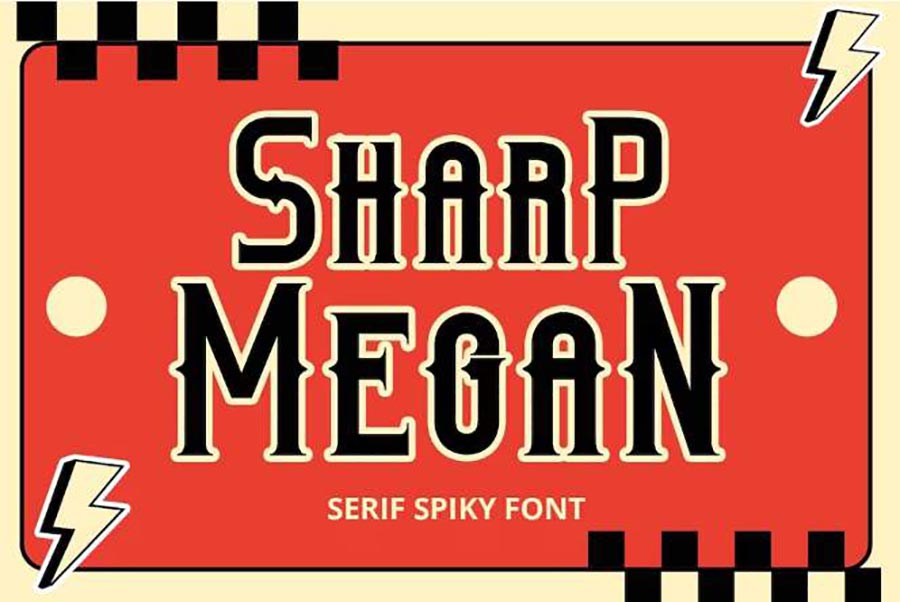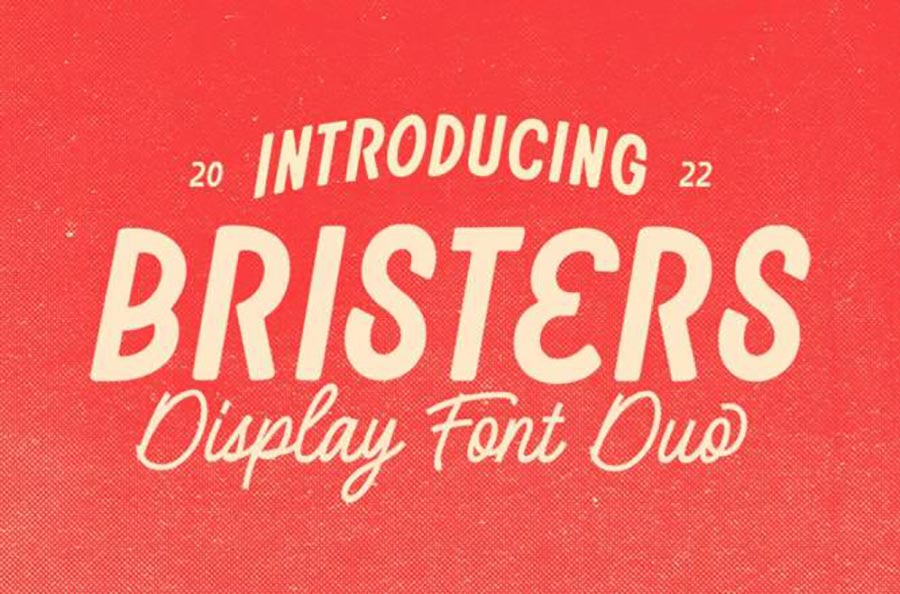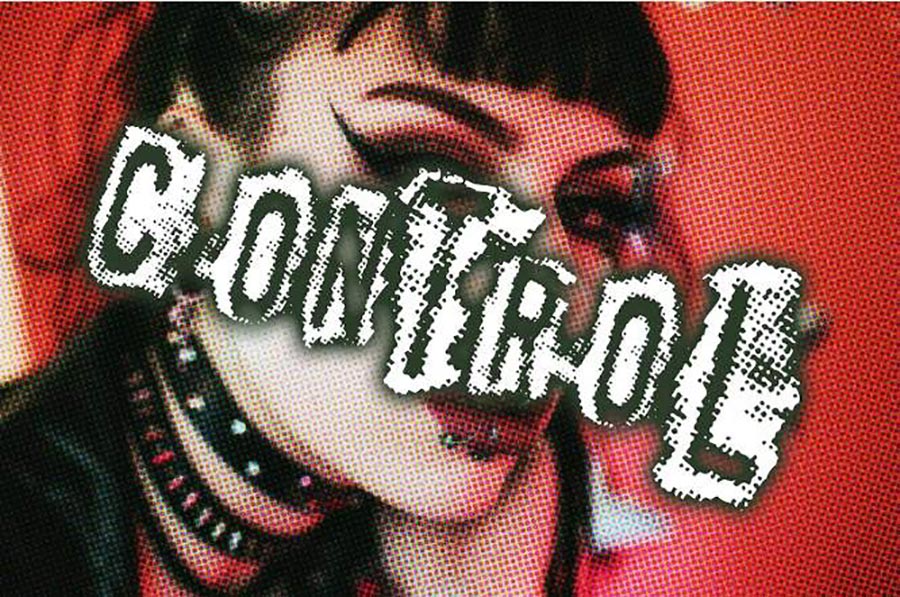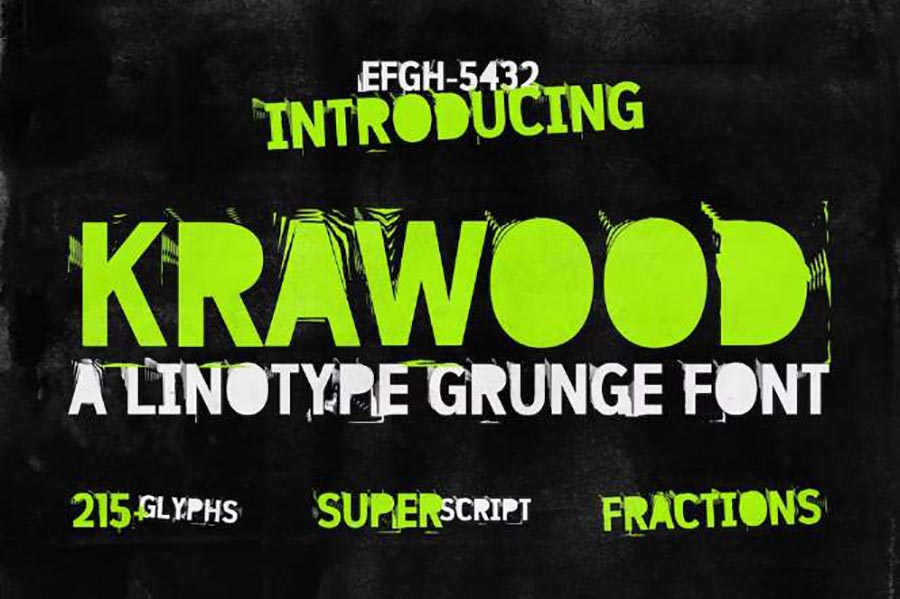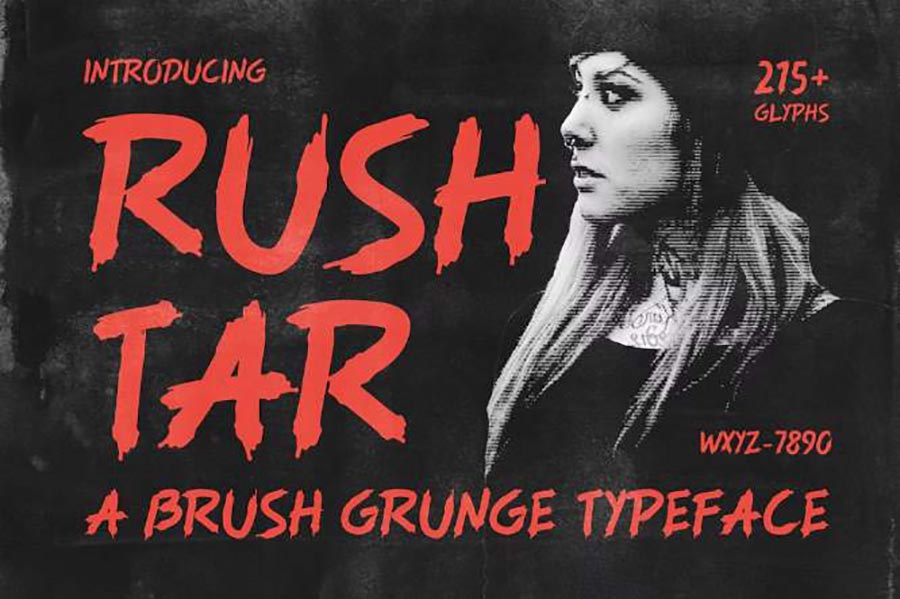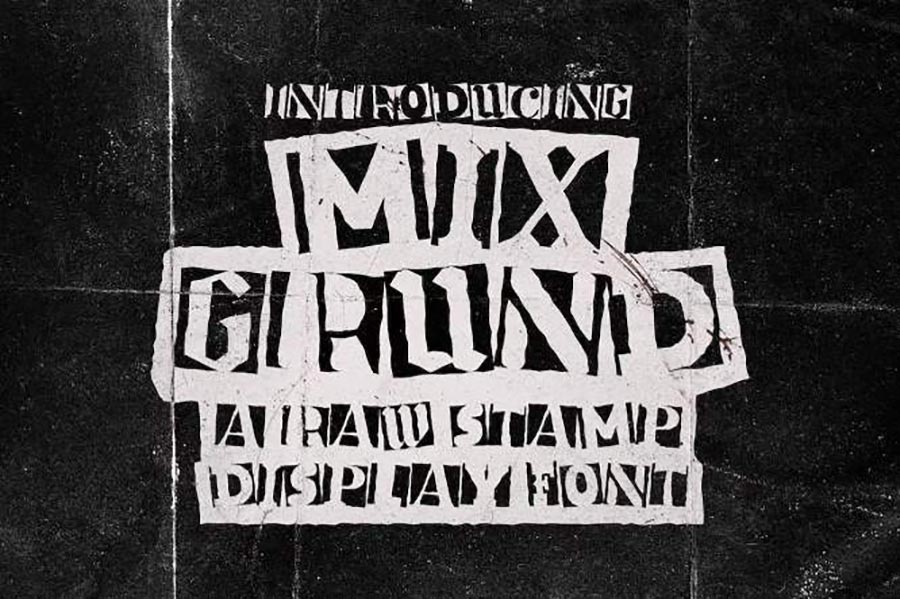
Chia Sẻ Tải Miễn Phí Fonts Punk Đẹp, Độc Đáo Nhất
Trong thế giới thiết kế đồ họa ngày nay, việc lựa chọn phông chữ phù hợp có thể tạo ra sự khác biệt lớn trong việc truyền tải thông điệp và phong cách của một thiết kế. Đặc biệt, các phông chữ mang phong cách Punk đã và đang thu hút sự chú ý của nhiều nhà thiết kế bởi tính độc đáo và nổi loạn của chúng.
Phông chữ punk là một trong những xu hướng thiết kế độc đáo và nổi bật, mang đến sự phá cách và sáng tạo trong lĩnh vực thiết kế đồ họa. Đặc điểm nổi bật của các phông chữ này là sự kết hợp giữa các yếu tố thô ráp, bất quy tắc và cá tính mạnh mẽ, tạo ra một phong cách rất riêng biệt. Các phông chữ punk thường sử dụng các đường nét không đối xứng, các ký tự được biến tấu một cách táo bạo, và thường đi kèm với các hiệu ứng như vỡ, xước hoặc loang lổ.
Sự độc đáo của phông chữ punk không chỉ nằm ở hình thức mà còn ở khả năng truyền tải thông điệp mạnh mẽ, làm nổi bật ý tưởng và thương hiệu mà nó đại diện. Trong bối cảnh thiết kế hiện đại, việc lựa chọn phông chữ punk phù hợp có thể giúp tạo nên ấn tượng sâu sắc và thu hút sự chú ý của người xem, đồng thời thể hiện được cá tính và phong cách riêng của nhà thiết kế.